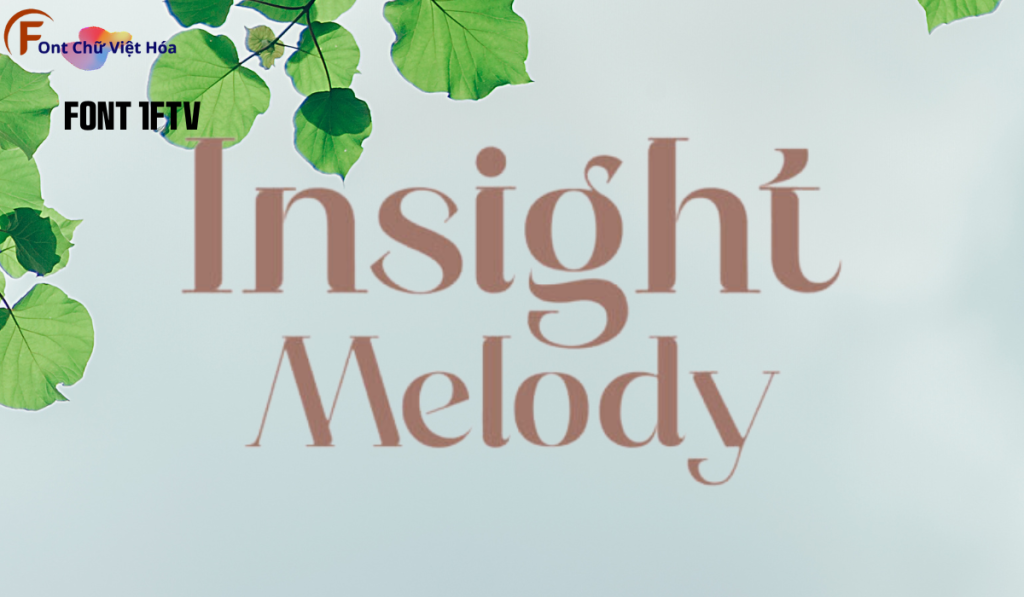
Font 1FTV Insight Melody
Font 1FTV Insight Melody là một font chữ độc đáo, thuộc bộ 1FTV, nổi bật với phong cách serif cổ điển và các đường nét thanh thoát, tinh tế. Thiết kế của 1FTV Insight Melody tập trung vào sự sang trọng và dễ đọc, đặc biệt phù hợp cho các thiết kế đòi hỏi tính thẩm mỹ cao như banner, poster, và logo. Với tỷ lệ chữ cân đối và các đường nét rõ ràng, font này tạo ra ấn tượng thị giác mạnh mẽ và giúp tối ưu hóa không gian trong thiết kế. Font này cũng đã được Việt hóa, mang đến sự linh hoạt và tiện dụng cho các dự án thiết kế bằng tiếng Việt.